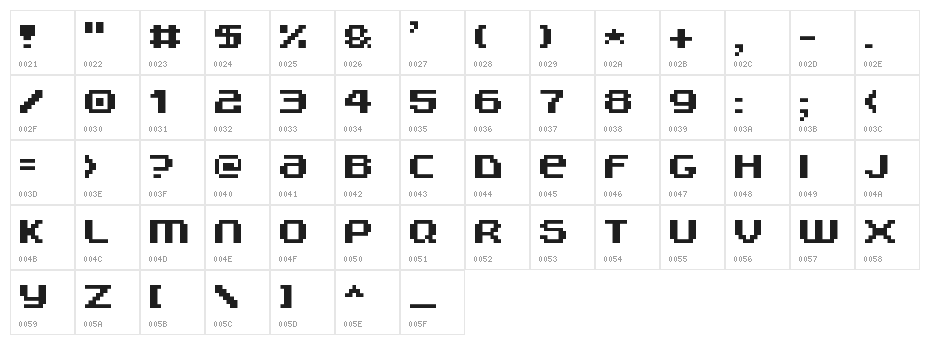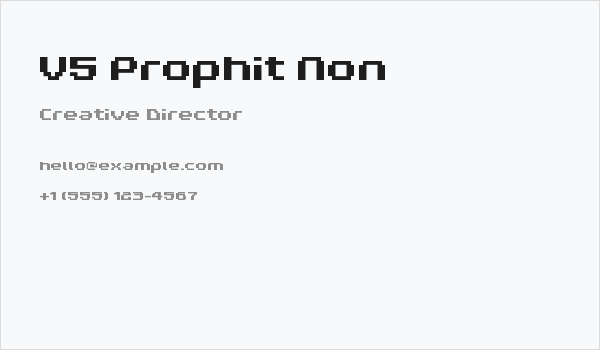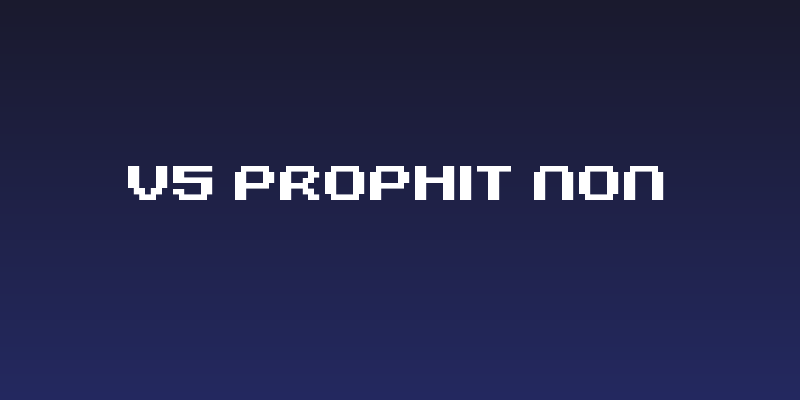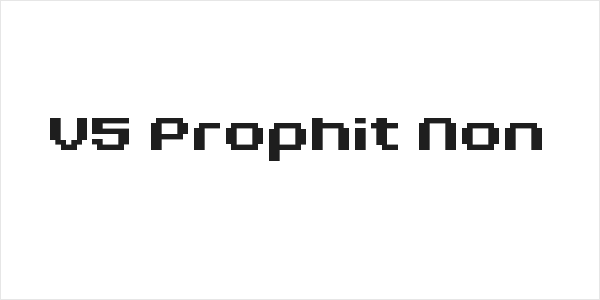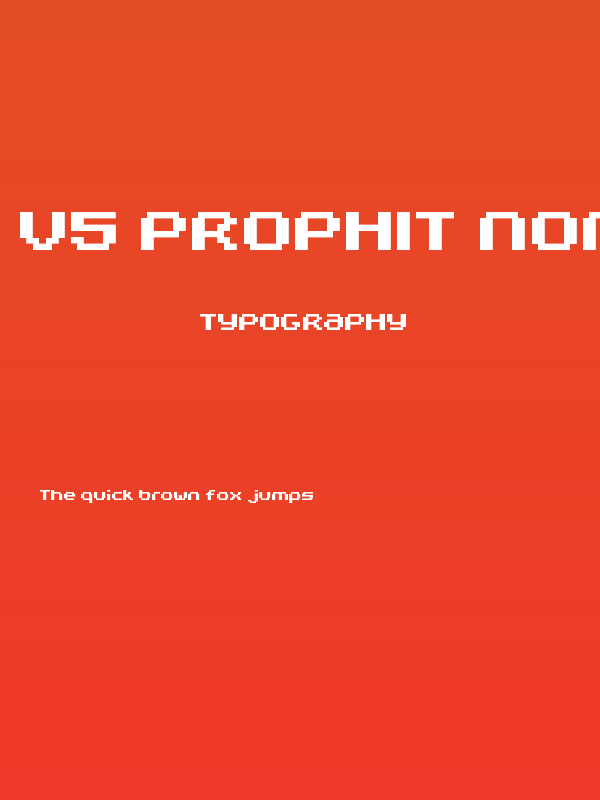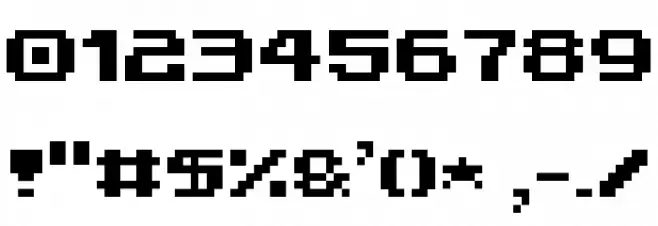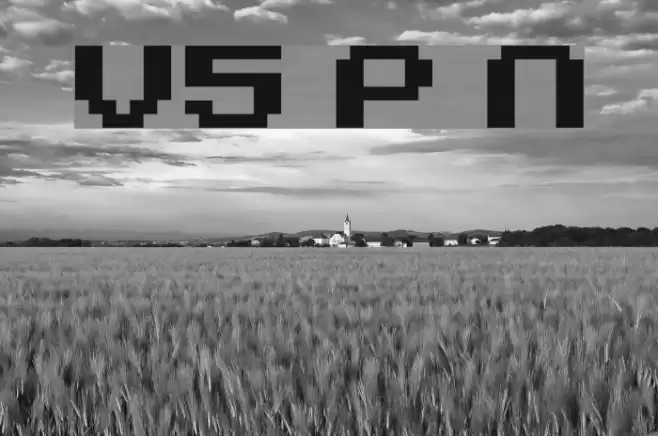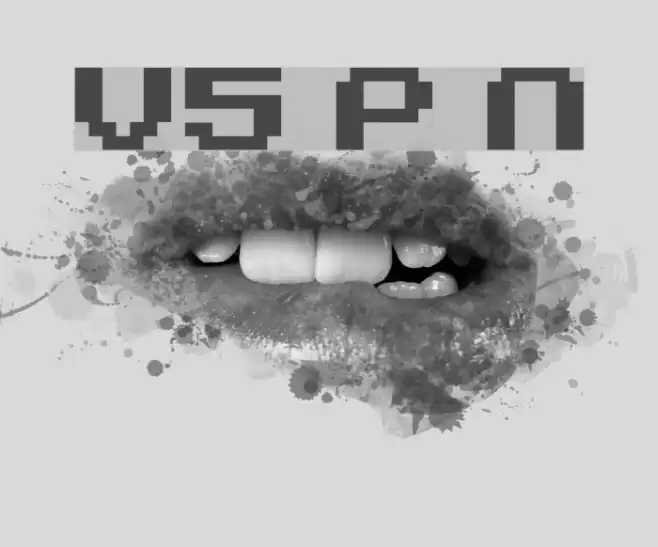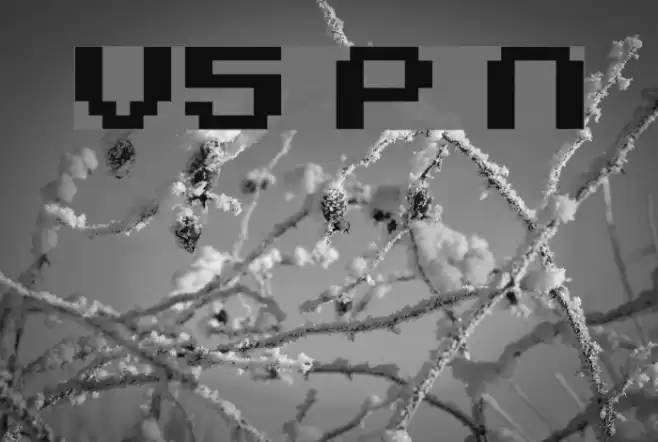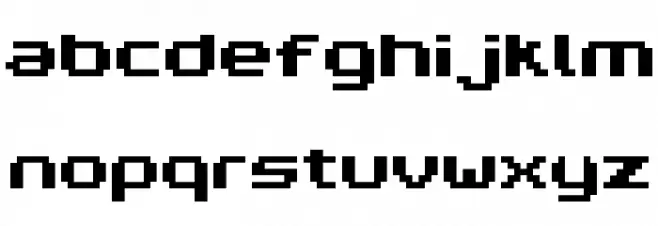
V5 Prophit Non Font
| श्रेणियाँ | Pixel |
| समग्र शैली | Retro, Digital |
| उपयोग का मामला | Headlines, Logos, Digital Art |
| सुझाए गए प्रोजेक्ट | Ideal for retro video game designs, digital art projects, and any creative work seeking a nostalgic, digital aesthetic. |